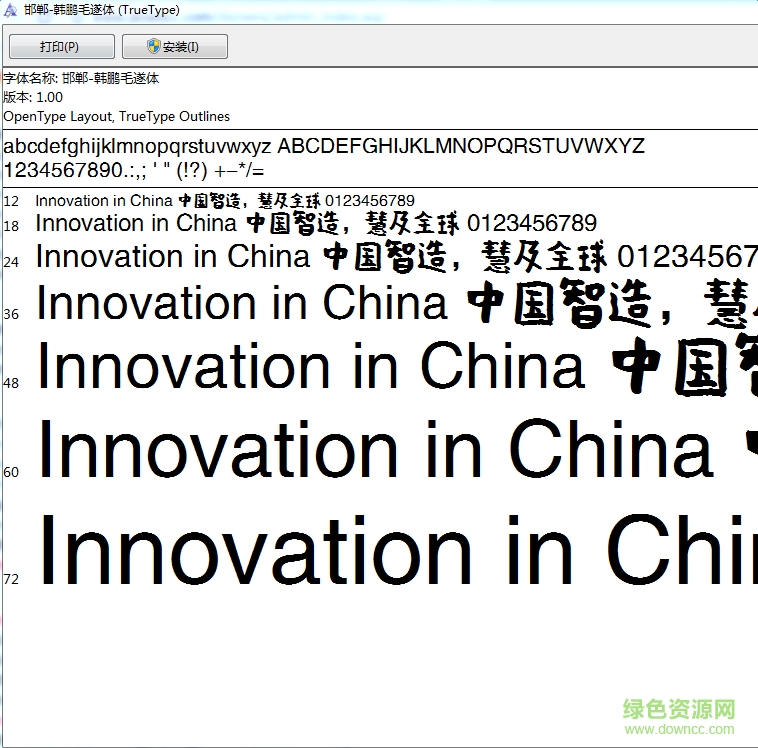
邯鄲韓鵬毛遂體字體是由古代邯鄲韓鵬為背景成立的一款漢儀字體,邯鄲韓鵬毛遂體憑借其獨(dú)特的風(fēng)騷筆畫(huà),給人十分有創(chuàng)意的感覺(jué),整體效果非常優(yōu)美,綠色資源網(wǎng)還有更多好看的免費(fèi)字體下載!
邯鄲韓鵬毛遂體超越了傳統(tǒng)思維模式,創(chuàng)造出新的書(shū)法藝術(shù)風(fēng)格,賦予書(shū)法特別的審美情趣,以其秀勁、爽利、古雅、飄逸之美獨(dú)領(lǐng)風(fēng)騷。袁體用筆一反秦漢以來(lái)幾千年的用筆規(guī)則,用筆直率簡(jiǎn)練,舒展挺拔,秀美爽利,與傳統(tǒng)的楷書(shū)和隸書(shū)的用筆有明顯的不同??芍^直逼秦漢另出一體,為五體之外的第六書(shū)體。其秀勁爽利飄逸的字體,創(chuàng)建了隸書(shū)秀勁派的書(shū)風(fēng)。
邯鄲韓鵬毛遂體字體盡顯毛遂體的風(fēng)騷藝術(shù),非常的爽利、秀勁,闡釋了真正的毛遂體魅力,喜歡的朋友歡迎到綠色資源網(wǎng)下載!